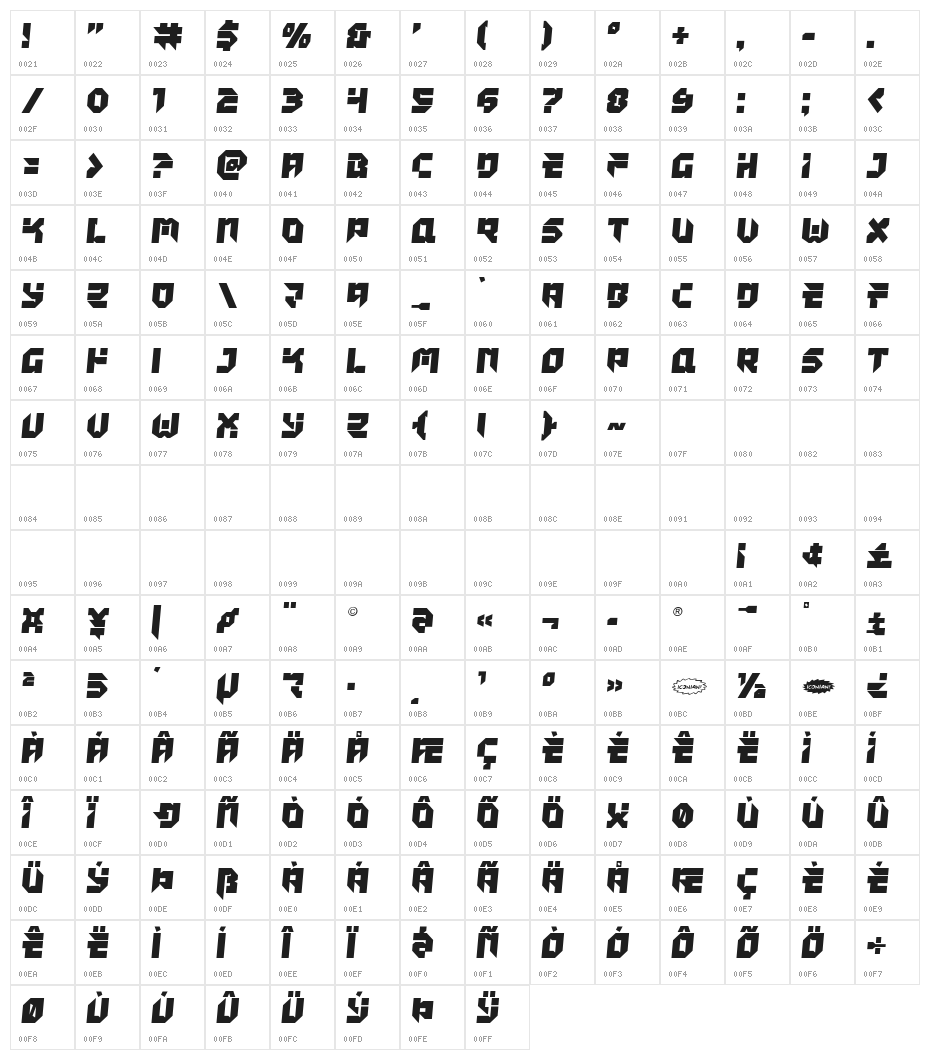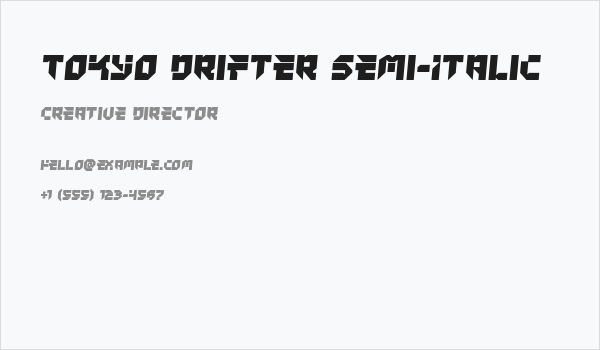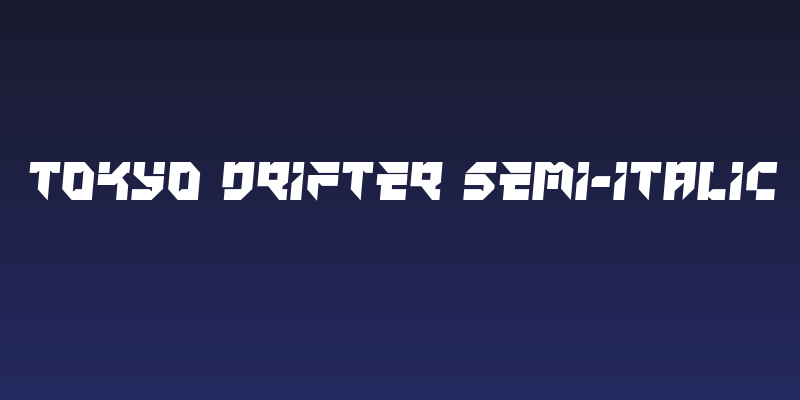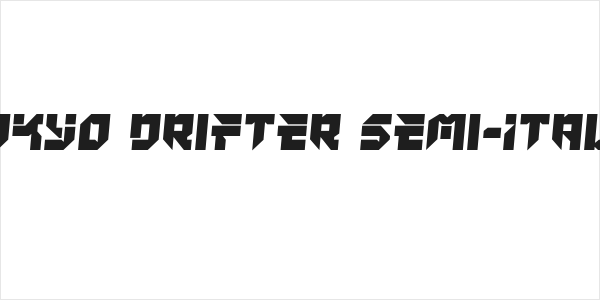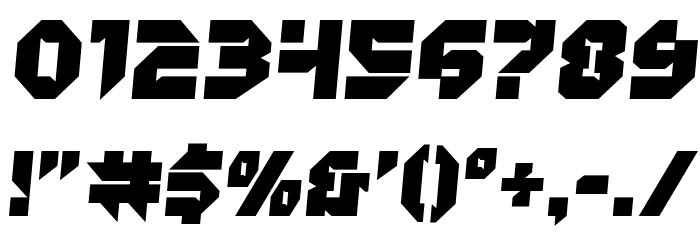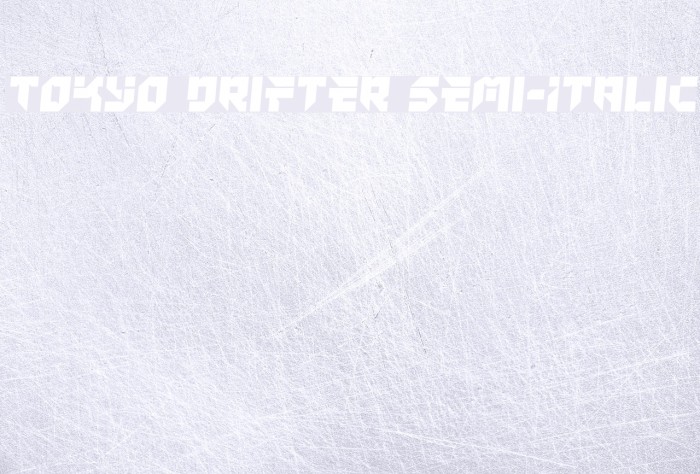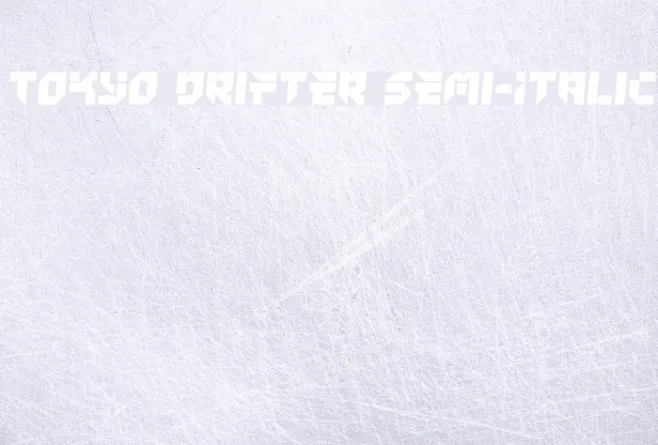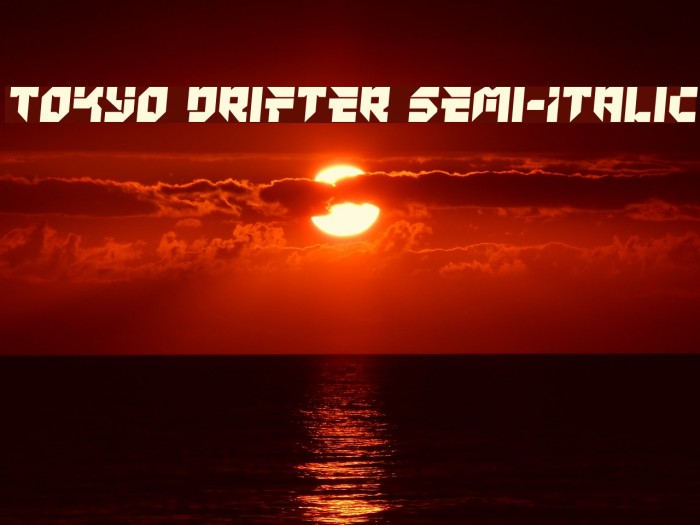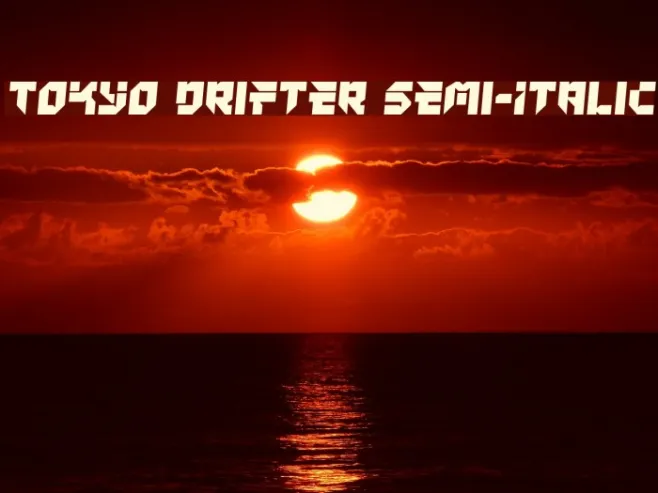
Tokyo Drifter Semi-Italic Font
| Proyectos propuestos | Ideal for branding, posters, video game graphics, and any project needing a modern, edgy look. |